مجموعة الخطوط: دليل إقران الخطوط للتصميمات الخاصة بك
عندما تنظر إلى شعار ، ما هو أول شيء تلاحظه في تصميمه؟ ربما اللون ونمط الخط.
ومدى جودة قراءة اسم العلامة التجارية ، ومدى جمال النص في استكمال الرمز الموجود في الشعار ، تعتمد جميعها على نمط الخط المستخدم في الشعار.
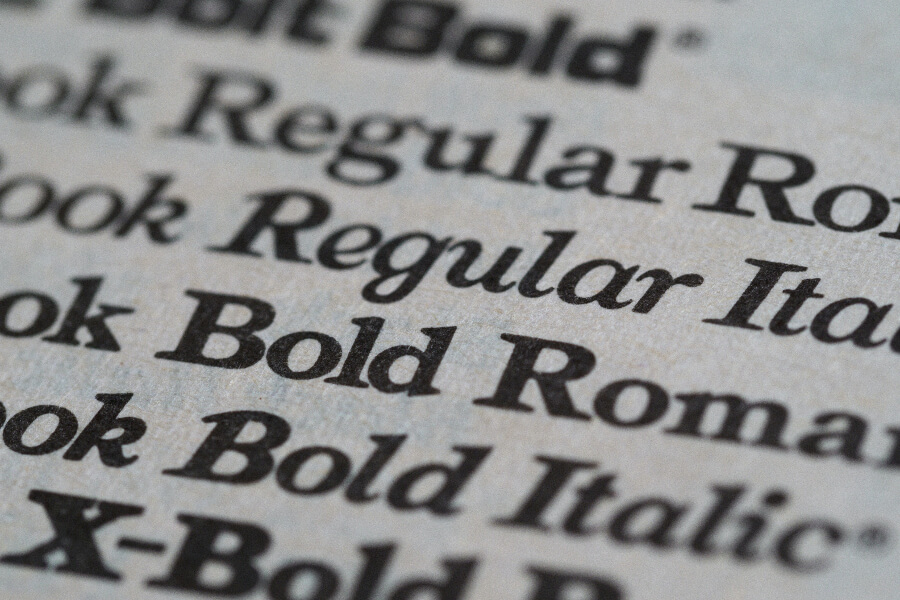
باختصار ، كل شيء ، من الانطباع الأول الذي يخلقه التصميم إلى مدى بقاء التصميم لا يُنسى ، يعتمد على نمط الخط المختار.
ولكن ، هذا هو المصيد. كل نمط خط له طابعه الخاص. لذلك ، عندما يتعين عليك اختيار مجموعة من خطين أو أكثر ، يجب أن تكون حذرًا بحيث يكون التأثير الكلي على النحو المنشود.
يقودنا هذا إلى سؤال ملح في عالم تصميم الرسوم: "كيف تجمع بين الخطوط لمشروع تصميم؟"
لكن قبل ذلك ، دعنا نصحح المصطلحات.
المحارف والخطوط والطباعة
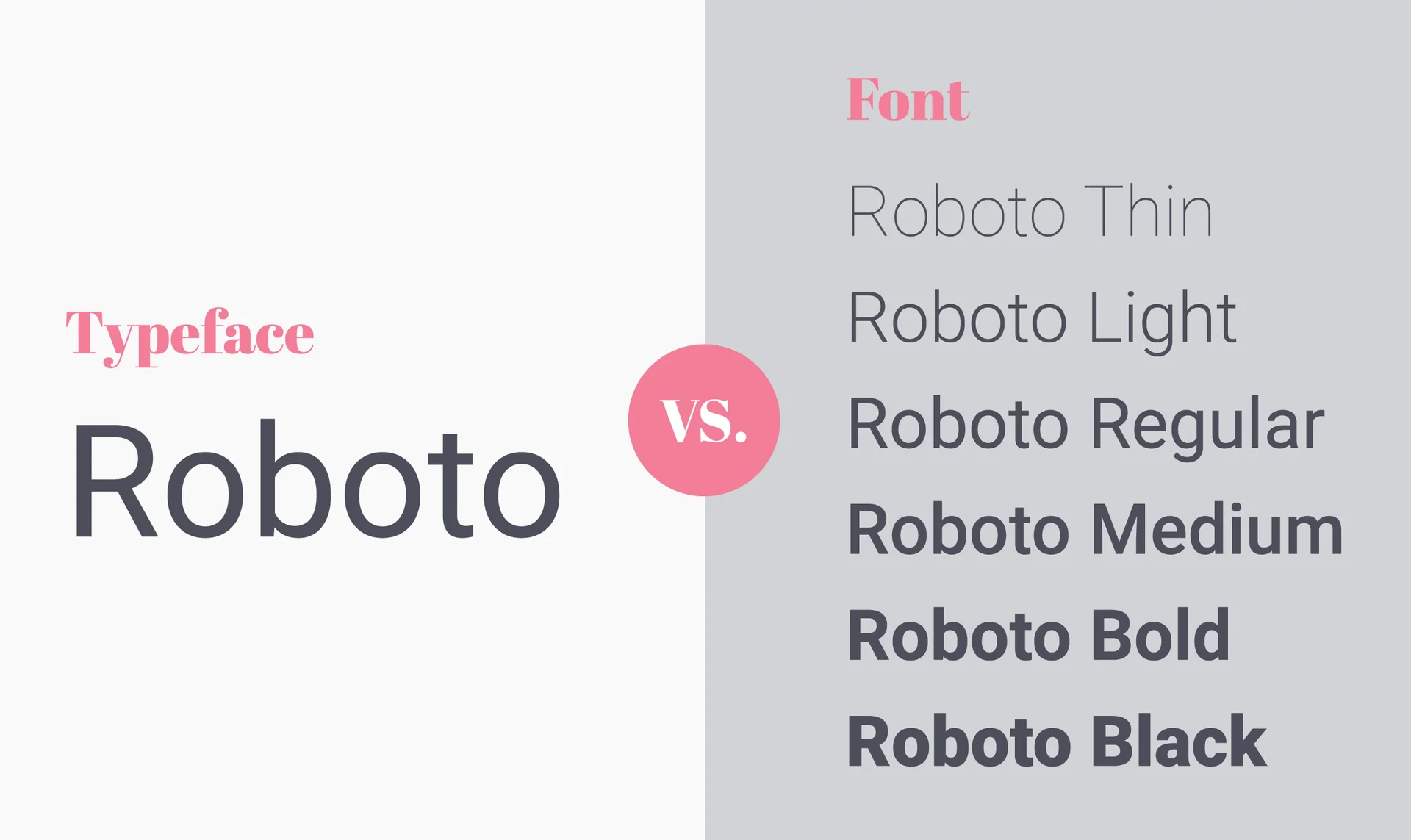
قد ينتهي بنا الأمر باستخدام مصطلحات الخط والخط والطباعة بالتبادل لكنها تعني أشياء مختلفة جدًا. وفهم الاختلافات يسهل على غير المصممين التواصل مع المصممين.
أضف إلى ذلك ، 74٪ من المسوقين يستخدمون المرئيات في أكثر من 70٪ من المحتوى الذي يستخدمونه للتسويق. وغالبًا ما تحتوي هذه العناصر المرئية على نصوص وصور. أثناء استخدام الصور لجذب الانتباه وإنشاء اتصال عاطفي ، يدعم النص الصور ويتأكد من توصيل الرسائل بوضوح.
لذا ، للتأكد من اختيارك للخطوط ومجموعات الخطوط المناسبة لتأسيس رسالة تصميمك ، دعنا نتحدث عن بعض المصطلحات الأساسية.
محرف
يشير "محرف" إلى أشكال وأنماط كل حرف أبجدي رقمي. وداخل الخطوط ، يمكن أن يكون لديك تصنيفات مثل serif ، و sans-serif ، والنص ، والزخرفة.
1. الخطوط Serif
لديهم خط رقيق أو سكتة دماغية صغيرة تمتد خارج الحرف. Times New Roman ، على سبيل المثال ، هو محرف سيريف. داخل خطوط serif ، هناك أسلوب قديم ، وانتقالي ، وحديث ، وألواح رقيق.
في الخطوط الرقيقة ذات الطراز القديم ، تكون ضربات الحروف كلها تقريبًا بنفس السماكة ولكن الرقيق رفيع ومدبب. في النمط الانتقالي ، هناك اختلاف طفيف بين الضربات الرفيعة والسميكة للحروف والرقيق. يظهر محرف serif الحديث أكبر قدر من الاختلاف بين الأشكال الرفيعة والسميكة للحدود. وعلى الرغم من أن هذه الأنماط الثلاثة تحتوي على خطوط رفيعة ، إلا أن أسلوب البلاطة الرفيعة يتميز بسمك الرقيق مثل السكتات الدماغية.
2. محارف Sans-serif
هذا الخط لا يحتوي على الرقيق في الحروف. بدلا من ذلك تبدو الحروف نظيفة وبسيطة. Arial و Helvetica هما خطان مشهوران من نوع sans-serif.
داخل محارف sans-serif ، تؤدي الاختلافات المستندة إلى عرض الحدود وأشكال الحروف إلى أربعة تصنيفات رئيسية: هندسية ، وشاذة ، وشائعة جديدة ، وإنسانية.
تبدو الخطوط الهندسية sans-serif أكثر تقريبًا وتماثلًا. كانت خطوط Grotesque من أقدم أنواع خطوط sans-serif التي أصبحت شائعة. يلتقط الاسم طابع هذه الخطوط حيث يجدها البعض غريبًا بالنظر إلى خيارات عرض الخطوط غير المتساوية للأحرف.
تتشابه خطوط Neo-grotesque sans-serif تمامًا مع الأنماط الانتقالية في محرف serif. وأخيرًا ، يشبه الأسلوب الإنساني في محرف بلا سيريف ضربات الخط. تشتهر هذه بوضوحها.
3. محارف البرنامج النصي
هذه تبدو وكأنها نص مكتوب بخط اليد ، مثل خط Lucida ، على سبيل المثال. يتم اشتقاق أشكال الحروف من ضربات تعتمد على القلم أو بالفرشاة. يُنظر إلى الاختلافات هنا بشكل أساسي على أساس ميل الضربات ، واختلافات الارتفاع إلى العرض ، ووجود أو عدم وجود الزخارف كما هو موضح في أنماط الخط.
4. المحارف الزخرفية
عندما تريد ثني القواعد والانطلاق في أسلوب الطباعة الخاص بك ، فقد تعمل خطوط العرض بشكل جيد. هذه لها تفاصيل دقيقة أو بيان تضيف لمسة مزخرفة. قد ينحرفون عن جميع القواعد التي تتبعها مع تصنيفات الخطوط الثلاثة الأخرى. قد لا تلمس بعض السكتات الدماغية الخط الأساسي وأحيانًا يكون ارتفاع x متنوعًا. لكن هل لها تأثير على الإطلاق!
الخطوط
الخطوط هي مجموعات فرعية من المحارف. كل من الأشكال الممكنة لمحرف هو خط. يمكن أن تكون الاختلافات في أوزان أو سمك الضربات التي تشكل الحروف. هذه تتراوح من متوسطة إلى رفيعة أو مائلة أو جريئة ، ويمكنها أيضًا دمج اختلافات بصرية أخرى مطبقة على كل ضربة وكل منحنى لكل حرف.
الطباعة
يحدد أسلوب الطباعة كيفية ترتيب الخطوط المختلفة أو أنواع الخطوط التي تجمعها لإنشاء تكوين عام. يتم الجمع بين المسافات بين كل حرف واختلافات الحجم والجوانب الأخرى بطريقة تجعل وضوح النص ومظهره متوازنين.
لذلك ، عندما نتحدث عن دمج الخطوط اليوم ، سنخبرك بكيفية إحضار محارف مختلفة في نفس الإطار وأيضًا كيفية إظهار الاختلافات داخل نفس المحرف.
تركيبة الخطوط: لماذا يجب عليك دمج الخطوط
ربما اشتريت خطًا أو اخترت خطًا مجانيًا يبدو جيدًا حقًا. وأنت مستعد تمامًا لتصميم إعلانك أو منشوراتك على مواقع التواصل الاجتماعي. ألا يكفي أن تستخدم نفس الخط بأحجام وألوان مختلفة؟ بينما يبدو من السهل التعامل مع خط واحد فقط ، إلا أن هناك سببين لعدم وجوب ذلك:
- قد يؤدي عدم وجود اختلاف في أنماط الخطوط إلى جعل التصميم يبدو رتيبًا
- ليست كل الخطوط مقروءة عند تصغيرها
تمامًا كما تبدو النوتات الموسيقية أفضل مع التقلبات ، تبدو التصميمات أفضل مع الاختلافات الدقيقة في أنماط الخطوط.
تلميحات حول تركيبة الخطوط لغير المصممين
إذن ، كيف تجعل هذه الخطوط والمحارف تعمل بانسجام لإيصال الرسالة المقصودة بوضوح؟ هيا نكتشف.
1. حدد الغرض وحدد التسلسل الهرمي المرئي
قبل أن تبدأ حتى في اختيار المحارف وتنوعات الخطوط داخلها ، قم بفصل نسختك عن التصميم إلى أقسام معقولة. على سبيل المثال ، العنوان والنص الأساسي وكلمات التركيز و CTA والتفاصيل الإضافية والعناوين الفرعية للحفاظ على التدفق.
من خلال تحديد الهدف من كل قسم نصي ، فأنت تقوم بإعداد التسلسل الهرمي المرئي لتصميمك. يعتمد أي جزء من النسخة يلفت الانتباه أولاً وأي نص سيقرأه العملاء في النهاية على مدى جودة تحديد التسلسل الهرمي المرئي.
هنا ، يجب أن يكون العنوان بخط ذو طابع قوي يلفت الانتباه. بالنسبة للنص الأساسي ، فأنت بحاجة إلى شيء يمكن قراءته حتى عندما يتعين عليك تقليص حجمه. يمكن أن تكون العناوين الفرعية مجرد شكل غامق أو مائل للنص الأساسي ولكن بحجم خط أكبر بشكل واضح. وبالنسبة للكلمات الرئيسية ، يمكنك استخدام خط عريض داخل الخط المختار.
2. اذهب مع التباين الكلاسيكي بين serif و sans-serif
أحد الأشكال الأكثر شيوعًا التي يحب المصممون استخدامها هو إبراز التباين من خلال الجمع بين محارف serif و sans-serif.
صممه كيمب
عندما تكون مهتمًا بالتفاصيل ، يمكنك بسهولة اختيار الخطوط الصحيحة داخل كل تصنيف من خلال مقارنة أشكال الحروف. تبدو المحارف التي تظهر أشكال حروفها متشابهة إلى حد ما متناغمة عند دمجها.
عندما يكون لديك نسخة طويلة ، يمكنك استخدام شيء غامق مثل slab-serif للرأس. ونظرًا لوجود العديد من أسطر النص ، فإنك تحتاج إلى التركيز على الوضوح. لذلك ، يمكنك استخدام شيء أكثر نظافة مثل محرف sans-serif الجديد البشع. يعمل هذا التباين بشكل خاص مع التصميمات الرقمية مثل منشورات الوسائط الاجتماعية أو حتى الإعلانات الرقمية والنشرات الإخبارية عبر البريد الإلكتروني.
ومع ذلك ، بالنسبة للتصميمات القائمة على الطباعة ، يتم اختيار خطوط serif المقروءة في الغالب للنص الأساسي ومحارف sans-serif محجوزة للرؤوس. في هذه الحالة ، سيكون خيار sans-serif الغريب الجريء خيارًا رائعًا للرؤوس. تبدو خطوط serif ذات النمط القديم بأشكال حروفها سهلة الانسيابية جيدة في النص الأساسي.
نصيحة Kimp: أحد أكثر الأماكن شيوعًا حيث ستجد هذا المزيج من خطوط serif و sans-serif سيكون تصميم شعار. يمكن أن يكون اسم علامتك التجارية والشعار أو النص الذي يوضح ما تفعله علامتك التجارية في خطوط متباينة بحيث تبرز تفاصيل كل منها. فقط تأكد من مواءمة شخصية الخط المختار مع شخصية علامتك التجارية.
هل تجد صعوبة في اكتشاف مجموعة الخطوط المناسبة لتصميم شعارك؟ قم بإجراء مكالمة مع فريق Kimp اليوم لمعرفة كيف يمكن أن يساعدك اشتراك التصميم غير المحدود في تصميم شعار مذهل لعلامتك التجارية.
3. إنشاء تباين دون غموض
يمكن أن تحدث التعارضات في التصميم عندما تكون جميع الخطوط التي تختارها قوية جدًا أو ضعيفة جدًا في شخصيتها لإنشاء تباين فعال. على سبيل المثال ، أنت تعلم أن خطوط sans-serif و slab serif الشائنة جريئة ومكتنزة. سيؤدي استخدام أحدهما للرأس والآخر للنص الأساسي إلى إجهاد شديد لعين القارئ.
يتنافس كلا الخطين على الاهتمام وتضيع الرسالة المراد نقلها في المعركة. حتى إذا قمت بتغيير حجم الخط أو أضفت شكلًا غامقًا إلى أحد هذه ، فلن يحدث فرق كبير.
يعد دمج الخطوط في نفس العائلة خيارًا شائعًا آخر. ولكن مرة أخرى ، لا يمكنك الجمع بين خطين أو أكثر من خطوط slab serif حيث ينتهي بهم الأمر جميعًا إلى كسر التسلسل الهرمي الذي تحاول تأسيسه.
4. الحصول على الرقم الصحيح
إذن كم عدد الخطوط التي يجب أن تجمعها حقًا؟ يمكن للمرء أن يكون عاديًا جدًا. ثلاثة ساحقة. اثنان هو مجرد حق. هناك اختلاف واضح في مظهر كل عائلة محرف. لذلك ، عندما تحاول الجمع بين ثلاثة منهم أو أكثر ، فقد يؤدي ذلك إلى حدوث فوضى بصرية.
صممه كيمب
نصيحة Kimp: اجمع بين محرفين فقط ثم اختر مجموعات خطوط متشابهة في كل منها للحصول على أفضل النتائج.
5. للحصول على تصميم خالي من الإزعاج ، عصا مع محرف واحد
إذا كنت تجد صعوبة في تجميع محرفين لتصميمك ، فلا بأس من العمل باستخدام محرف واحد فقط. يمكنك استخدام التباين في أوزان الضربات لتحقيق التأثير المفضل لديك.
صممه كيمب
في المثال أعلاه ، الرسالة واضحة ومقروءة بسبب خط sans-serif المستخدم. وللتأكيد على كلمة التركيز ، تم استخدام الأحرف الكبيرة. يتم استخدام اختلافات اللون ووزن الحد للفت الانتباه إلى CTA. يبدو التصميم العام متماسكًا بينما يتم تحديد الأقسام المختلفة أو الأدوار المختلفة لمقتطفات النص بوضوح.
6. استخدم الحجم لتحديد ترتيب القراءة
أثناء إنشاء التناقضات ، يتمثل أحد الأهداف الرئيسية في تحديد ترتيب القراءة لأقسام النص المختلفة بوضوح. إذا كان هناك قسم معين تريد أن يقرأه القراء أخيرًا ، فاستخدم أحجام خطوط أصغر لهذا القسم. هذا لا يشير إلى أن هذه أقسام نصية ذات أهمية أقل. في معظم الحالات ، تميل إلى أن تكون معلومات يجب أن تبقى في أذهان القارئ.
صممه كيمب
يستخدم معظم المصممين هذا التكتيك ل CTAs أو معلومات الاتصال في الإعلانات المطبوعة. في بطاقة العمل أعلاه على سبيل المثال ، عندما يكون النص الأخير الذي يراه القارئ هو الأزرار الاجتماعية ، فمن المرجح أن يظل هذا في ذهنه. نتيجة لذلك ، قد يبحثون عن العمل على وسائل التواصل الاجتماعي ويتابعونه أيضًا.
يمكنك دائمًا إضافة زر تمييز أو اختيار لون مختلف بحيث لا يمر أصغر قسم نصي دون أن يلاحظه أحد.
7. لا تتجاهل الحالة المزاجية لرسالتك
أثناء انشغالك بالتركيز على جوانب التباين والوضوح ، لا يمكنك تجاهل الحالة المزاجية أو الشخصية العاطفية التي تحتاجها لتصميمك. ألق نظرة على المثال أدناه.
صممه كيمب
بالنسبة إلى مخطط المعلومات هذا ، يمكن أن يكون العنوان بخط مكتنزة serif لجذب الانتباه. لكن استخدام محرف نصي أنيق هو ما يجعل التصميم يبدو كاملاً. يجب أن يخبر الرأس المشاهد بشكل أساسي عن موضوع الصورة.
في هذه الحالة ، هو رسم بياني به الكثير من النصوص. لذلك ، إذا نجح العنوان في إثارة الاستجابة العاطفية المقصودة على الفور ، فهناك فرص أفضل لأن ينتبه المشاهد لبقية النص.
8. إظهار التباين من خلال تعديلات قرن الحروف
عندما لا يمكنك إظهار الكثير من التباين في حجم الخط أو الأوزان ، يمكنك دائمًا اللعب بتقنين الأحرف. عندما تقوم بزيادة التباعد بين الحروف ، فإن قسم النص يلفت الانتباه حتى إذا كنت تستخدم محارف محايدة وأوزان أرق.
صممه كيمب
في الصورة أعلاه ، بالنسبة لاسمي العروس والعريس ، تم زيادة حجم النص للفت الانتباه إلى القسم. لكن هذا لا يكسر النهج البسيط للتصميم بسبب الاستخدام الحكيم لتقنين الأحرف.
نصيحة Kimp: أثناء محاولتك توسيع أو تجميع الأحرف في النص ، تأكد من عدم وجود حل وسط بشأن الوضوح. قد يؤدي التباعد الكبير بين الأحرف عندما يكون حجم الخط صغيرًا جدًا بالفعل إلى إضعاف التأثير أو يصعب أحيانًا التمييز بين تباعد الكلمات وتباعد الأحرف.
هل ترغب في تحقيق أقصى استفادة من تباينات المسافات بين الحروف لإنشاء تصميمات بيان لوسائل التواصل الاجتماعي أو الإعلانات المطبوعة؟ اعمل مع فريق Kimp وقم بإنجاز جميع تصميماتك من خلال اشتراك تصميم غير محدود برسوم ثابتة.
9. استخدم خطوط العرض لإضافة بعد جديد
صممه كيمب
عندما تحتاج إلى تصميم شعار بسيط أو إعلان LinkedIn احترافي ، يمكنك دائمًا الجمع بين serifs و sans-serifs للحصول على التأثير المطلوب. ولكن هل سبق لك أن واجهت موقفًا استخدمت فيه جميع التقنيات الصحيحة ولكن التصميم لا يزال يبدو أنه يفتقر إلى الشخصية التي تصورتها؟ لست وحدك.
عندما تحتاج إلى إضافة القليل من الإثارة إلى تصميمك أو عندما تحتاج إلى إنشاء شخصيات قوية مثل التأثيرات الرجعية أو المشاعر الانتقائية ، يمكنك دائمًا اختيار خطوط العرض. هذه تأتي في جميع الأشكال والأحجام. بعضها يحتوي على مخططات فقط وبالتالي يسهل السماح للخلفية بالسيطرة على التصميم. ويمكن إضافة البعض للإدلاء ببيان.
10. إظهار اختلافات حجم واضح
صممه كيمب
عندما تختار مجموعات الخطوط التي تبدو متشابهة جدًا ، فأنت بحاجة إلى تغيير الأوزان وأحجام الخطوط لإظهار التباين بشكل فعال. لن يؤدي تغيير الحجم بمقدار نقطتين أو ثلاث نقاط فقط إلى إحداث فرق كبير. يعمل هذا مع تمييز الكلمات الرئيسية ولكن ليس لتمييز النص الرئيسي والنص. أنت بحاجة إلى هذا التمييز لإنشاء خطاف مرئي يجذب الانتباه ويجعل الناس يتوقفون وينظرون إلى تصميمك.
إلهام التصميم لمجموعة الخطوط
لفهم القواعد التي ذكرناها أعلاه بشكل أفضل ، ولمعرفة مكان استخدامها ، إليك بعض الإلهام في التصميم:
المصدر: رسائل البريد الإلكتروني الجيدة حقًا
في البريد الإلكتروني أعلاه من Cracker Barrel ، يتماشى خط البرنامج النصي الجميل تمامًا مع موضوع إهداء عيد الحب في البريد الإلكتروني. حجم الخط الكبير يجعلك تشعر بالراحة عند فتح البريد الإلكتروني. وللرسالة الفعلية ، تم استخدام خط sans-serif الخالي من الإزعاج لتسهيل قراءة النص بالكامل.
المصدر: ويكيميديا
المثال الأكثر شيوعًا للجمع بين خطوط serif و sans-serif لتحقيق توازن مرئي هو شعار Louis Vuitton. يجسد خط serif إرث العلامة التجارية ويمنحها خط sans-serif لمسة معاصرة لإظهار كيف تطورت العلامة التجارية.
المصدر: Facebook Ad Library
الإعلان أعلاه هو مثال على اختيار أنماط الخطوط للحفاظ على تناسق العلامة التجارية. عندما تختار خطوطًا لإقرانها لإعلاناتك ، يمكن أن يكون أحد الخطوط هو نفس محرف تصميم شعارك.
صممه كيمب